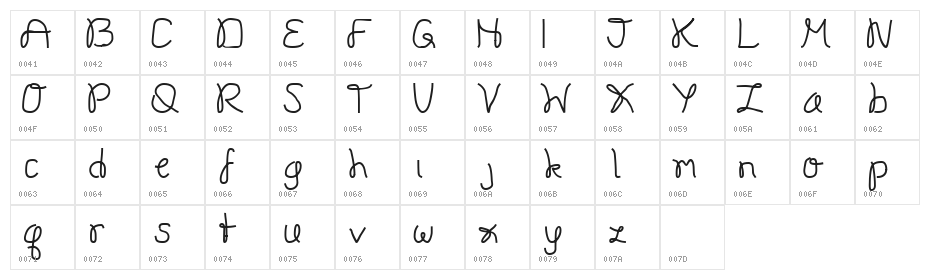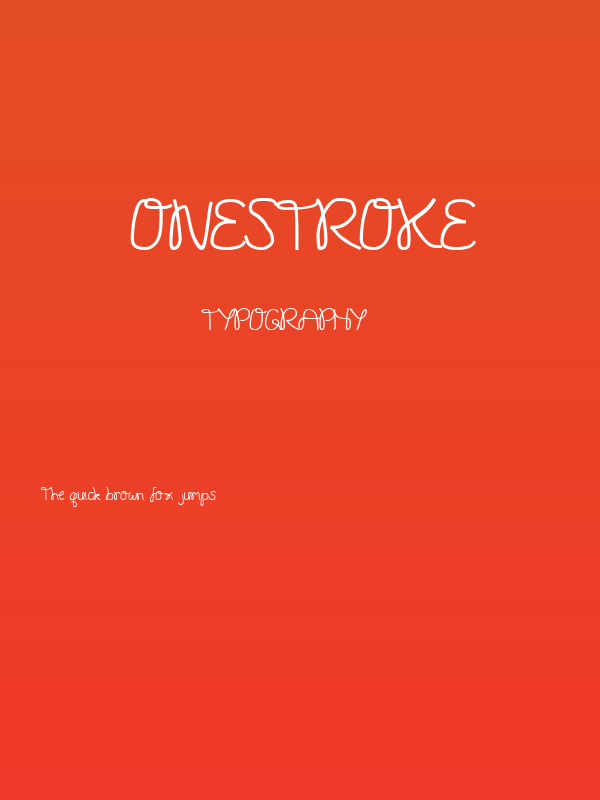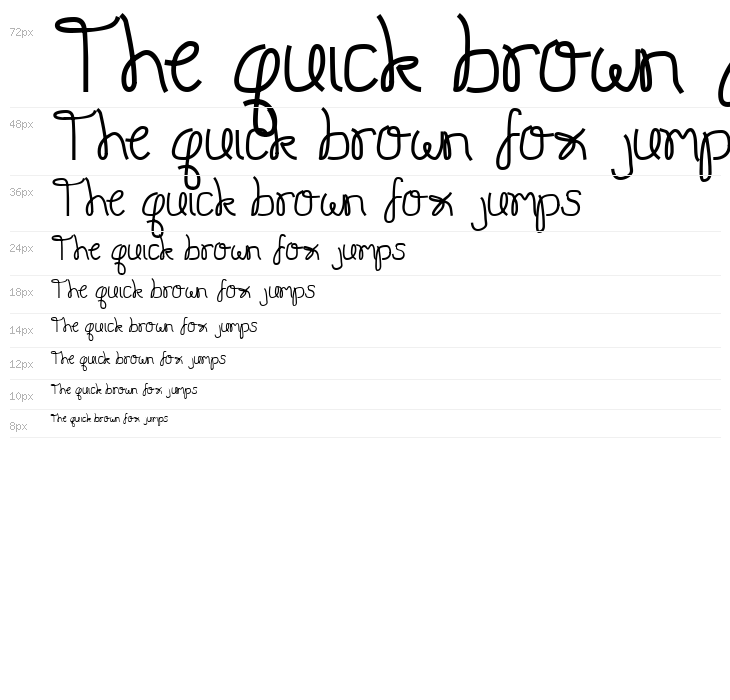
Onestroke Font
| Caso d'uso | Logos, Headlines, Artistic projects |
| Progetti proposti | Ideal for creative projects such as logo design, branding, and artistic posters. It can also be used in digital art and modern advertising campaigns to add a unique touch. |